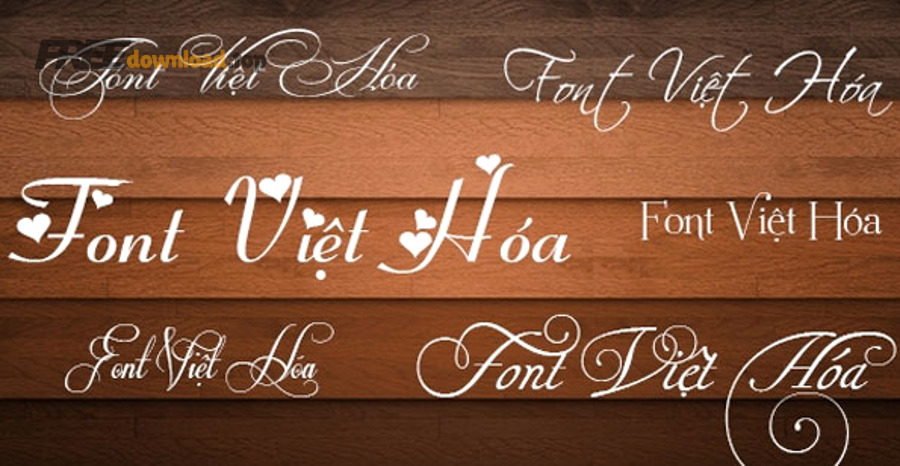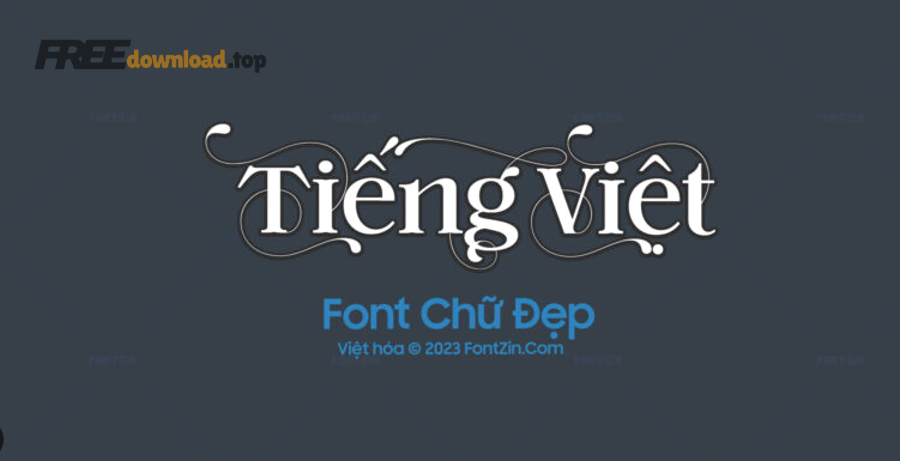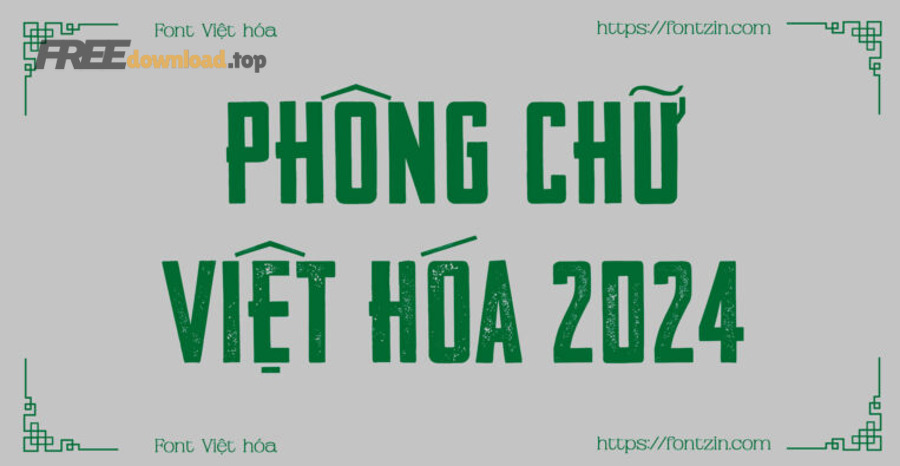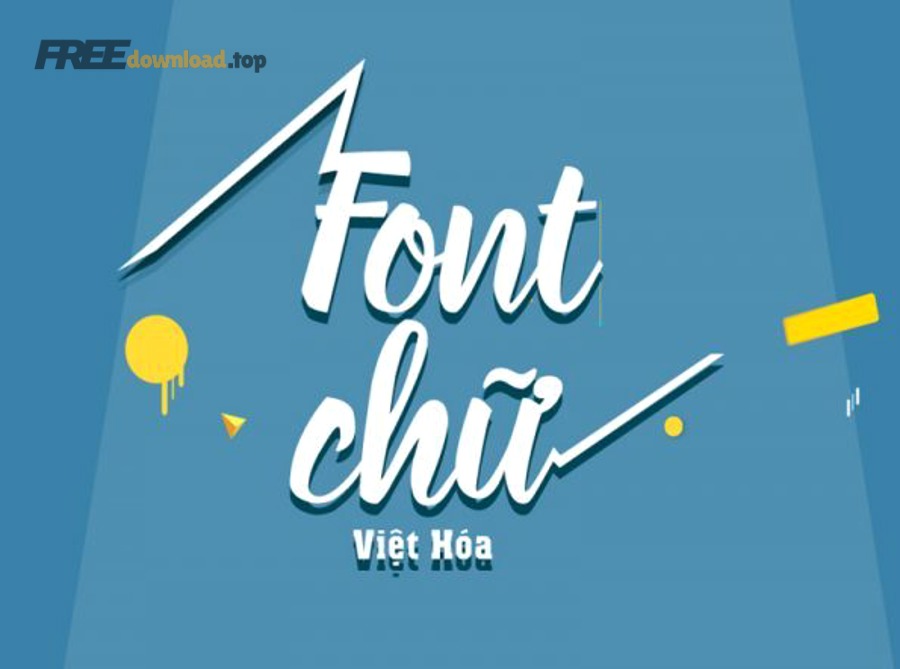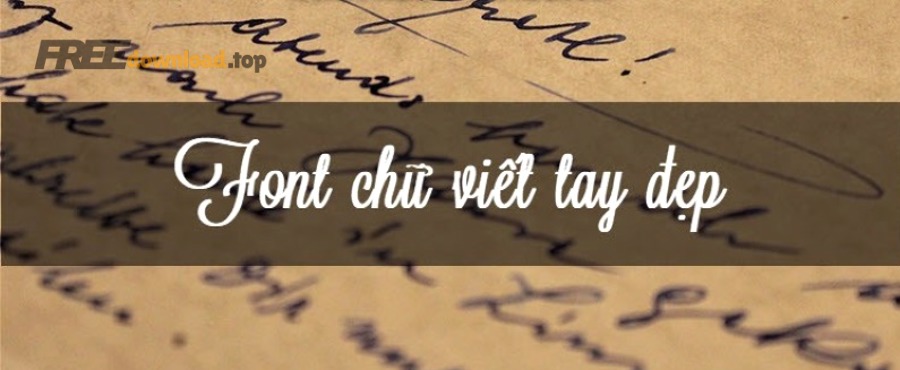
Chọn font tiếng Việt đẹp, tránh font xấu cho người thiết kế
Font tiếng Việt đẹp là bộ chữ hiển thị dấu đầy đủ, đọc rõ ở nhiều kích thước và giữ được cảm giác “mượt” khi nhìn lâu, سواء là dùng cho văn bản hay thiết kế. Nếu bạn đang tìm “font tiếng Việt đẹp”, mục tiêu thường là chọn được kiểu chữ vừa đẹp mắt vừa không làm dấu bị rối hoặc khó đọc.
Bên cạnh yếu tố thẩm mỹ, nhiều người còn quan tâm tính ứng dụng: dùng được trên Windows/macOS, đồng bộ khi gửi file cho người khác, và tương thích tốt với Word, PowerPoint, Photoshop, Illustrator, Figma hoặc Canva.
Một ý định phổ biến khác là muốn có “bộ font” theo mục đích: font cho tiêu đề, font cho nội dung dài, font cho UI/website, và font cho in ấn—mỗi nhóm sẽ có tiêu chí chọn khác nhau.
Giới thiệu ý mới, dưới đây là cách đánh giá, chọn, cài đặt và phối hợp font tiếng Việt sao cho vừa đẹp vừa ổn định trong thực tế sử dụng.
Font tiếng Việt đẹp là gì và “đẹp” được đánh giá thế nào?
Font tiếng Việt đẹp là font hỗ trợ đầy đủ ký tự tiếng Việt (dấu và chữ đặc biệt), có tỷ lệ chữ dễ đọc và giữ dấu cân đối, nhờ đó nhìn “mượt” ở cả màn hình lẫn in ấn mà không gây mỏi mắt.
Để bắt đầu, bạn cần hiểu “đẹp” trong font thường là tổng hợp của tính đọc được (readability) và tính phù hợp ngữ cảnh (context fit), chứ không chỉ là kiểu chữ lạ mắt.
Mẫu chữ và sắp chữ minh hoạ yếu tố đọc được và thẩm mỹ của font
Cụ thể hơn, tiếng Việt có hệ dấu dày (dấu sắc, huyền, hỏi, ngã, nặng; và dấu mũ, dấu trăng), nên một font “đẹp” phải xử lý dấu đúng vị trí, không chạm nhau, không bị lệch khi tăng/giảm cỡ chữ.
Ví dụ, khi bạn gõ “tối ưu hoá trải nghiệm”, hãy zoom 100% và 200% để xem dấu có bị “nhảy” hay không; đồng thời test ở 12–14pt (văn bản) và 28–48pt (tiêu đề) để kiểm tra độ cân đối.
Quan trọng hơn, font đẹp còn cần “nhịp điệu” tốt: khoảng trắng giữa chữ (spacing), khoảng cách dòng (leading) và độ dày nét (stroke contrast) không làm chữ bị bệt khi đọc dài.
Tiêu chí chọn font tiếng Việt đẹp cho in ấn và màn hình?
Để chọn font tiếng Việt đẹp đúng mục đích, hãy kiểm tra 5 tiêu chí chính: hỗ trợ ký tự tiếng Việt, độ rõ nét trên màn hình, khoảng cách chữ hợp lý, hệ đậm/nghiêng đầy đủ và giấy phép sử dụng phù hợp.
Tiếp theo, bạn nên phân biệt nhu cầu “đọc dài” và “tạo điểm nhấn”, vì mỗi nhu cầu sẽ ưu tiên tiêu chí khác nhau.
Văn bản dài minh hoạ nhu cầu chọn font dễ đọc cho tiếng Việt
Bảng này chứa các tiêu chí cốt lõi khi chọn font tiếng Việt và cách kiểm tra nhanh để tránh chọn nhầm.
Tiêu chí Vì sao quan trọng với tiếng Việt Cách kiểm tra nhanh
Hỗ trợ ký tự tiếng Việt (Unicode) Thiếu glyph sẽ gây lỗi hiển thị hoặc mất dấu Gõ câu có đủ dấu: “Trời mưa, đường trơn, nhớ đội mũ bảo hiểm.”
Độ rõ nét (screen rendering) Nét mảnh + dấu nhiều dễ bị nhòe ở cỡ nhỏ Test 12–14pt trên màn hình 100% zoom
Khoảng cách chữ (spacing/kerning) Dấu khiến chữ dễ bị “chật”, nhìn rối So sánh các cặp chữ: “VA, To, Tr, ưỡ”
Độ cao x-height và tỷ lệ X-height hợp lý giúp đọc nhanh, không mỏi Đọc đoạn 5–7 dòng ở 14–16px (web/UI)
Hệ font đầy đủ (weights/styles) Thiết kế cần nhiều cấp độ nhấn Kiểm tra có Regular/Medium/Semibold/Bold/Italic
Ngoài ra, với in ấn, bạn cần chú ý độ tương phản nét và độ “đằm” của chữ khi in ra giấy; trong khi đó với UI/website, ưu tiên là độ rõ ở kích thước nhỏ và tính đồng nhất khi hiển thị đa thiết bị.
Tóm lại, chọn font đúng tiêu chí sẽ giúp bạn tiết kiệm rất nhiều thời gian chỉnh sửa về sau, đặc biệt khi dự án có nhiều định dạng xuất file khác nhau.
Nên chọn serif hay sans-serif cho tiếng Việt?
Serif thường mạnh về cảm giác trang trọng và đọc dài trên ấn phẩm, còn sans-serif thường tốt hơn cho màn hình và UI; với tiếng Việt, lựa chọn tối ưu phụ thuộc vào cỡ chữ, môi trường hiển thị và độ dày nét để dấu không bị rối.
Để hiểu rõ hơn, hãy nhìn quyết định này theo 3 tiêu chí: độ đọc ở cỡ nhỏ, “khí chất” thương hiệu và khả năng phối cặp với font khác.
Minh hoạ văn bản và sách, phù hợp so sánh serif và sans-serif
Cụ thể, sans-serif (như Inter, Roboto, Open Sans, Be Vietnam Pro) thường có nét gọn, spacing dễ chịu, phù hợp cho giao diện và nội dung web. Trong khi đó, serif (như Lora, Merriweather, Noto Serif) có chân chữ tạo nhịp đọc tốt ở bài dài và in ấn, nhưng cần chọn loại có dấu tiếng Việt cân đối để tránh cảm giác “nặng đầu”.
Tuy nhiên, nếu bạn dùng serif cho tiêu đề lớn, hãy kiểm tra dấu ở 36–60pt vì các dấu như “ỗ, ẫ, ệ” dễ thành điểm “đụng” nếu font thiết kế chưa tối ưu cho tiếng Việt.
Ngược lại, sans-serif ở cỡ nhỏ (12–14px) cần chú ý độ mở của chữ (aperture) và chiều cao x-height; font quá hẹp sẽ khiến dấu dày đặc và khó đọc khi lướt nhanh.
Như vậy, không có lựa chọn “đúng tuyệt đối”: UI/web thường ưu tiên sans-serif; bài dài hoặc ấn phẩm trang trọng có thể ưu tiên serif; còn thiết kế thương hiệu có thể phối cả hai để tạo hệ thống chữ linh hoạt.
Có cần kiểm tra mã hoá Unicode khi copy/paste tiếng Việt không?
Có. Dù phần lớn hệ thống hiện nay dùng Unicode, bạn vẫn nên kiểm tra khi dán từ nguồn cũ hoặc file lạ. Nếu thấy ký tự biến dạng, hãy chuẩn hoá văn bản về Unicode và thử lại bằng một font hỗ trợ tiếng Việt đầy đủ.